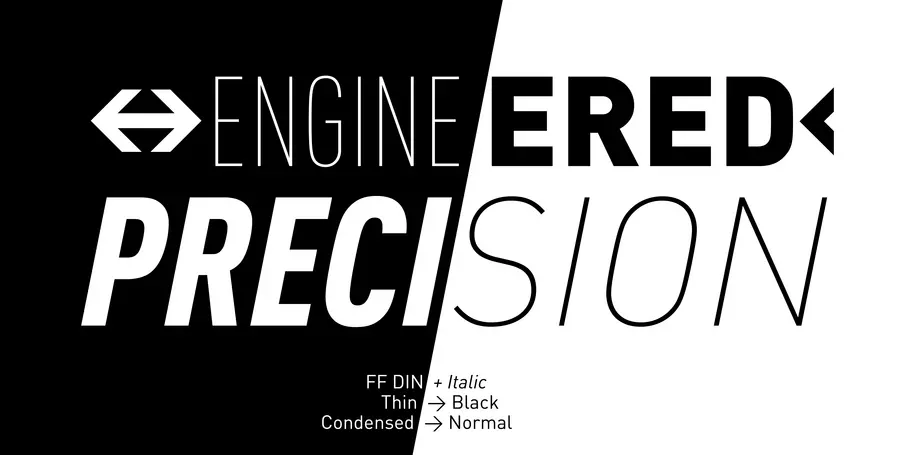
FF DIN Variable.
Más FF DIN que nunca.
La precisión es el mantra de FF DIN, y FF DIN Variable no es ninguna excepción a esta filosofía de diseño. FF DIN Variable te ofrece más FF DIN que nunca. Las fuentes variables desafían los límites de la tecnología para ofrecer al personal creativo una herramienta para integrar variaciones muy específicas que quedan bien en cualquier espacio de diseño.
FF DIN: la famosa, fiel y primera reedición de DIN 1451. FF DIN tiene su origen en los modelos de letras del estándar alemán DIN 1451 y se considera la tipografía estándar perfecta debido a su diseño metódico y especializado.
FF DIN Variable te ofrece más FF DIN que nunca. Las fuentes variables desafían los límites de la tecnología para ofrecer al personal creativo una herramienta para integrar variaciones muy específicas que quedan bien en cualquier espacio de diseño. FF DIN Variable supone un gran paso adelante en materia de ingeniería, ya que combina el diseño técnico de FFN DIN con la fluidez y el estilo casi orgánico de las fuentes variables.
FF DIN, disponible tanto en redonda como en cursiva, tiene mucho más que ofrecer con la llegada de la nueva era de la tecnología tipográfica. Aunque FF DIN Italic es una redonda inclinada, se le han aplicado correcciones ópticas para hacerla un poco más fina y estrecha. Como resultado, es un estilo que destaca de forma sutil.
FF DIN Variable es una fiel representación del ADN de su familia, y se ha prestado mucha atención para conseguir que sus nuevas instancias fueran coherentes con los pesos más conocidos. La precisión es el mantra de FF DIN, y FF DIN Variable no es ninguna excepción a esta filosofía de diseño. Produce una tipografía con un ajuste excepcional y títulos animados y expresivos para cualquier diseño.
Un sinfín de estilos para una tipografía inteligente e impactante.
Albert-Jan Pool nació en Ámsterdam el 9 de julio de 1960. Tras estudiar en la Royal Academy of Arts (KABK) de La Haya con Gerrit Noordzij, se marchó a Hamburgo en 1987 y trabajó con Scangraphic y URW. Desde 1994, lleva su propio estudio, Dutch Design, y diseña tipografías, como FF OCR y FF DIN, así como tipos de letras corporativas para Jet/Conoco, C&A y HEM/Tamoil.
Antonia Cornelius es una diseñadora de tipografía y comunicación, docente, autora e investigadora alemana con especial interés en la legibilidad y la fluidez. Estudió diseño de la comunicación centrado en el diseño tipográfico con Jovica Veljović en la Universidad de Ciencias Aplicadas de Hamburgo. Justo después de terminar su máster, Antonia se unió a Dutch Design para ampliar la familia FF DIN con FF DIN Slab. Además, se dedicó incansablemente a diseñar el contorno de FF DIN y FF DIN Stencil para convertirlas en fuentes variables.
Achaz Reuss se graduó como diseñador de comunicación en la Universidad de Ciencias Aplicadas de Hamburgo en 1983. Trabajó como diseñador tipográfico en URW y fundó su propia agencia de diseño, Reuss Design, en 1995, especializada en diseño y tipografía corporativos. Diseñó los tipos de letras de marca de NIVEA y Milram. FontShop publicó su familia tipográfica FF Qtype en 2004. En 1995, trabajó en los cinco primeros pesos de la tipografía FF DIN de Albert-Jan Pool y diseñó FF DIN Stencil, que se lanzó en 2022.